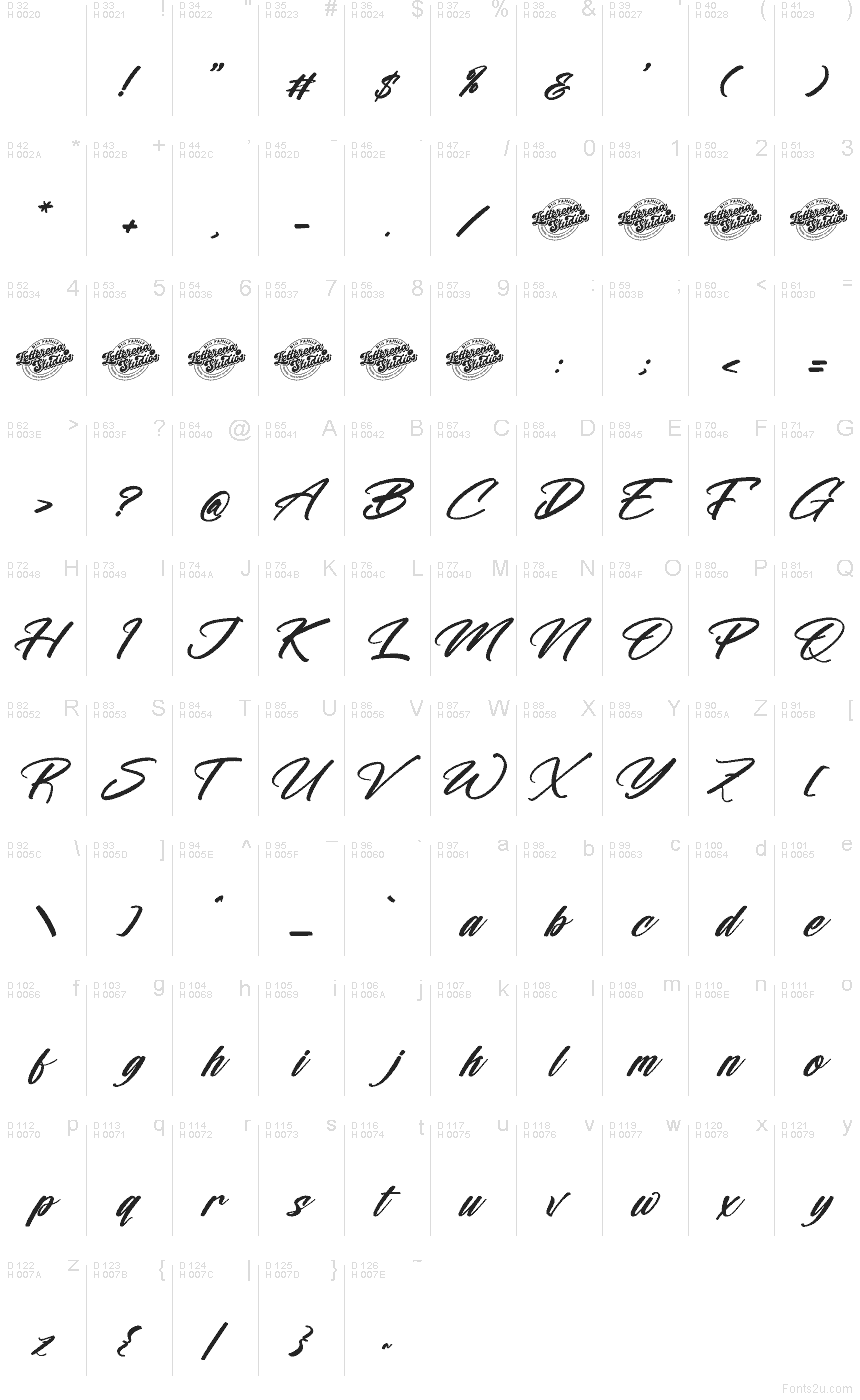
Malbonte Blackwell DEMO VERSION Italic
Malbonte Blackwell od Glorytype to darmowy krój kaligraficzny, który urzeka lekkością współczesnej kaligrafii ślubnej. Litery są mocno pochylone i płynnie łączą się w długich, wyrazistych pociągnięciach, mieszając szerokie linie z cienkimi łączeniami oraz kilkoma efektownymi zawijasami na początku i końcu, dzięki czemu całość zachowuje powietrzny, a nie przesadzony rytm.
Doskonale pasuje do brandingu, opakowań butikowych, zaproszeń, edytoriali modowych i treści do mediów społecznościowych, gdzie ręcznie pisany charakter jest ważniejszy niż formalna sztywność. Jako darmowy font, świetnie sprawdza się również w nagłówkach, szkicach logo i krótkich cytatach graficznych, ponieważ wysokie pętle i wydłużone linie nadają nawet krótkim słowom dynamiki.
Malbonte Blackwell od Glorytype to darmowy font kaligraficzny.